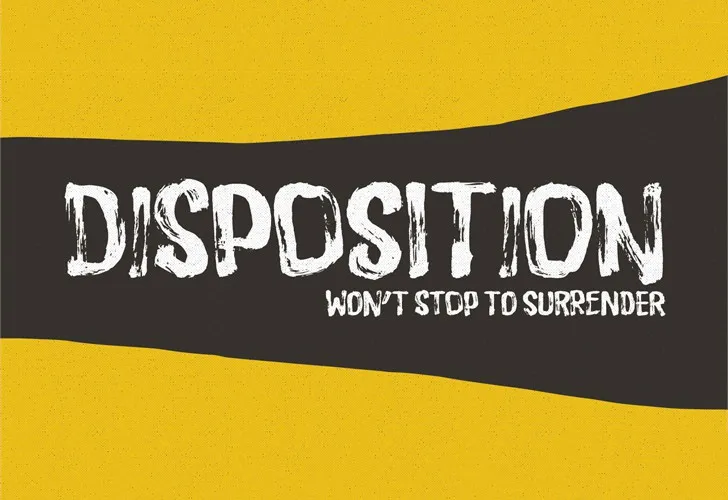
A fonte ‘Disposition Font’ é uma paixão para designers digitais amantes do handmade. Embora pareça apenas mais uma fonte, ela se revela ser única e imprevisível. Com seis versões diferentes para cada letra, você pode encontrar inúmeras maneiras criativas de usar esta fonte. A funcionalidade chamada de alternâncias contextuais faz com que a fonte mude entre as várias versões conforme você digita. A ‘Disposition Font’ é perfeita para designs como convites, headlines, posters e placas onde um aspecto desbotado de tinta à mão seja necessário. Com apenas uma descrição original em inglês informativa e convidativa, a fonte já está pronta para transformar seu design em algo único e artesanal. Não importa o projeto que você esteja criando, a ‘Disposition Font’ oferece um estilo inconfundível e diversidade suficiente para torná-lo visualmente imediatamente reconhecível.